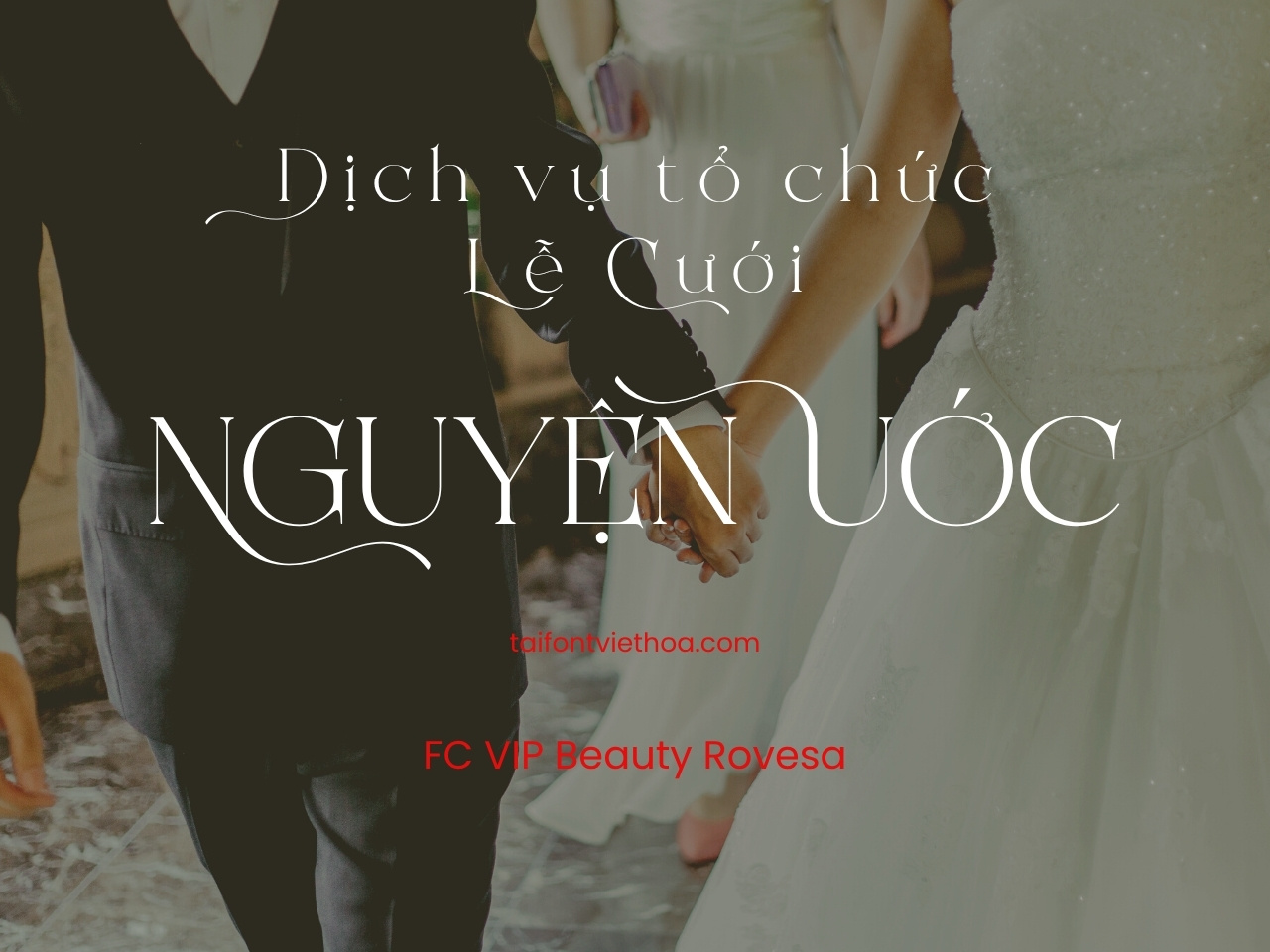
Giới thiệu về font Beauty Rovesa và phiên bản Việt hóa
FC Beauty Rovesa là phiên bản Việt hóa hoàn toàn riêng biệt từ font gốc “Beauty Rovesa” – một thiết kế serif tinh tế đến từ Brandsemut Studio (Indonesia), nổi bật với sự pha trộn giữa vẻ đẹp cổ điển và hình thức hiện đại. Font được giới thiệu lần đầu trên các nền tảng như Creative Fabrica và FontBundles vào năm 2022, và nhanh chóng trở thành lựa chọn phổ biến trong các thiết kế thương hiệu cao cấp, bìa sách, thời trang và mỹ phẩm. Với khả năng hỗ trợ hơn 75 ngôn ngữ Latin, Beauty Rovesa mang đến cảm giác sang trọng nhưng vẫn mềm mại và dễ tiếp cận.
Không giống với “1FTV VIP Beauty Rovesa”, phiên bản FC Beauty Rovesa được cộng đồng Font Chuẩn Việt hóa một cách độc lập, với toàn bộ bảng Unicode tiếng Việt được vẽ lại và tinh chỉnh thủ công. Các dấu thanh và ký tự đặc biệt được thiết kế khéo léo để giữ trọn vẹn vẻ thanh lịch, không làm lệch bố cục tổng thể. Font này được taifontviethoa.com tuyển chọn và kiểm duyệt kỹ lưỡng, dành riêng cho những nhà thiết kế Việt Nam đang tìm kiếm một kiểu chữ serif hiện đại, giàu tính thẩm mỹ và có khả năng ứng dụng cao trong các ấn phẩm chuyên nghiệp.
Đặc điểm thiết kế nổi bật và ứng dụng thực tế
Beauty Rovesa sở hữu cấu trúc chữ mềm mại, độ tương phản rõ rệt giữa nét thanh – nét đậm, cùng các đầu chữ có đường cong mềm uyển chuyển. Thiết kế kiểu serif giúp tạo cảm giác sang trọng, dễ đọc ở mọi kích thước. Các chữ cái in hoa đặc biệt được nhấn mạnh, phù hợp với các tiêu đề, logo hoặc ấn phẩm thương hiệu đòi hỏi tính thẩm mỹ cao. Font cũng được bổ sung nhiều glyphs đặc biệt, giúp nhà thiết kế linh hoạt hơn trong việc thể hiện ý đồ sáng tạo.
Beauty Rovesa là lựa chọn lý tưởng cho các lĩnh vực như thiệp cưới, bao bì mỹ phẩm, ảnh cưới – dã ngoại, ngành bất động sản cao cấp, thời trang và ẩm thực sang trọng. Ngoài ra, nó cũng phù hợp với các thiết kế mùa lễ hội như Giáng sinh, Tết, Valentine hoặc các thương hiệu truyền thông dành cho phái nữ.